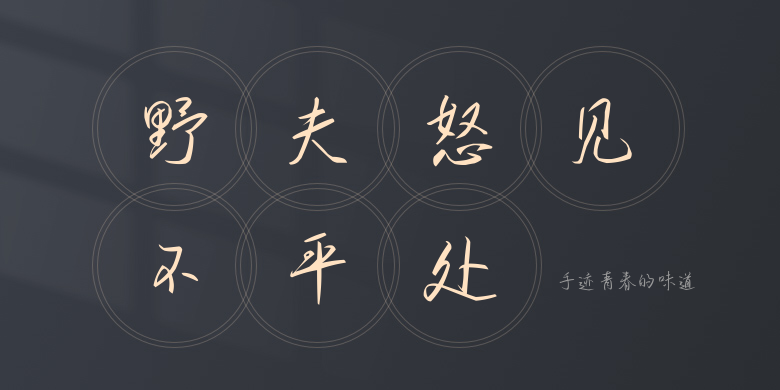
手迹青春的味道
手迹青春的味道,这款字体结构工整、笔画清晰,兼顾美观与易读性,适用于标题、正文、海报、包装、LOGO 等多种场景。字形优雅稳定,风格百搭耐看,适配日常排版与创意设计,让文字呈现更舒适、更具质感。手迹青春的味道一笔一画,皆是细节,以均衡的比例、流畅的线条打造舒适视觉体验,字形端正大气,风格简约现代。无论是商业设计、品牌宣传还是日常排版,都能轻松驾驭,让文字更有格调与力量。手迹青春的味道字体下载。